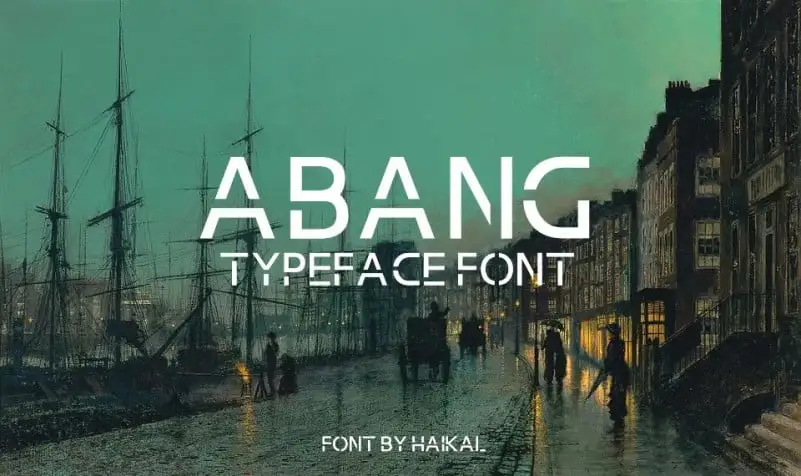
Abang Display Font – Fonte Grátis
Abang Display Font
Abang Display Font é uma fonte criada pelo designer Graphicfresh que se destaca pela sua simplicidade moderna e futurista. Ideal para diversos projetos, incluindo logo design, marca personalizada, web design, embalagens, redes sociais e muito mais! Com uma tipografia abrangente que incorpora letras maiúsculas, números e símbolos, Abang é perfeita para quem busca uma fonte de efeito visual atraente. Esta fonte é ideal tanto para iniciantes quanto para designers experientes que procuram um estilo limpo, contemporâneo que combina bem em qualquer projeto digital ou impresso.